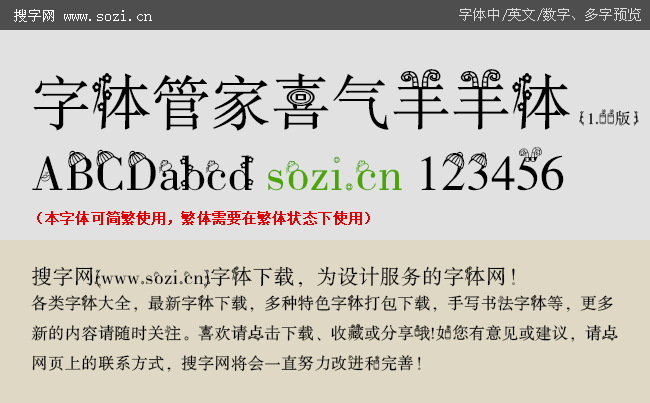
字體管家喜氣羊羊體
搜字網(wǎng)給大家提供一款字體管家喜氣羊羊體中文字體下載。這款字體是以宋體字為原形,字體間加入了卡通圖案裝飾。使端正簡(jiǎn)潔的宋體具有變化,增添了趣味性,是一款非?蓯(ài)的卡通字體,適合兒童書(shū)刊、商品包裝、海報(bào)設(shè)計(jì)等廣告設(shè)計(jì)場(chǎng)合使用。